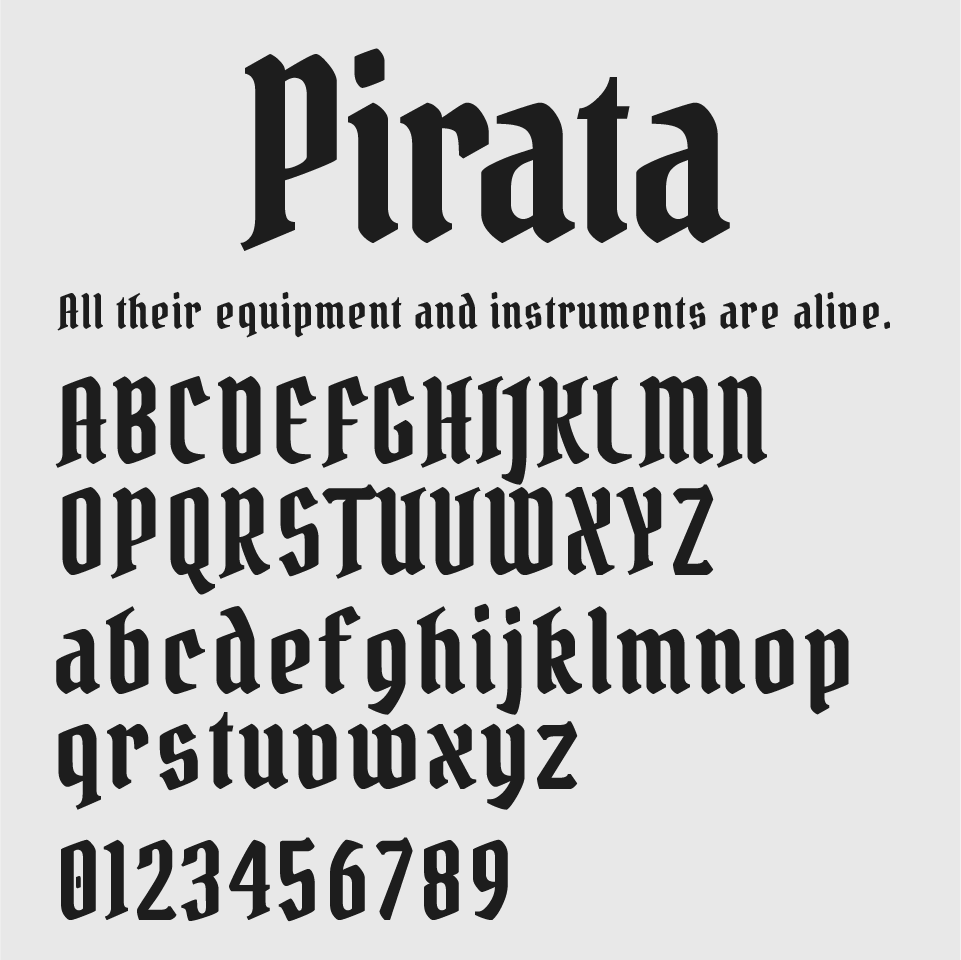
Pirataフォントは、切り立ったようなシャープな造形が特徴のブラックレター系フォントです。
直線的で鋭角なエレメントが力強く、まるで中世の紋章や古文書に刻まれた文字の雰囲気があります。重厚で誇り高い雰囲気があり、クラシカルな印象の中にもどこかリズムがあり、タイトルやブランドロゴに個性を持たせたいときにもぴったりです。